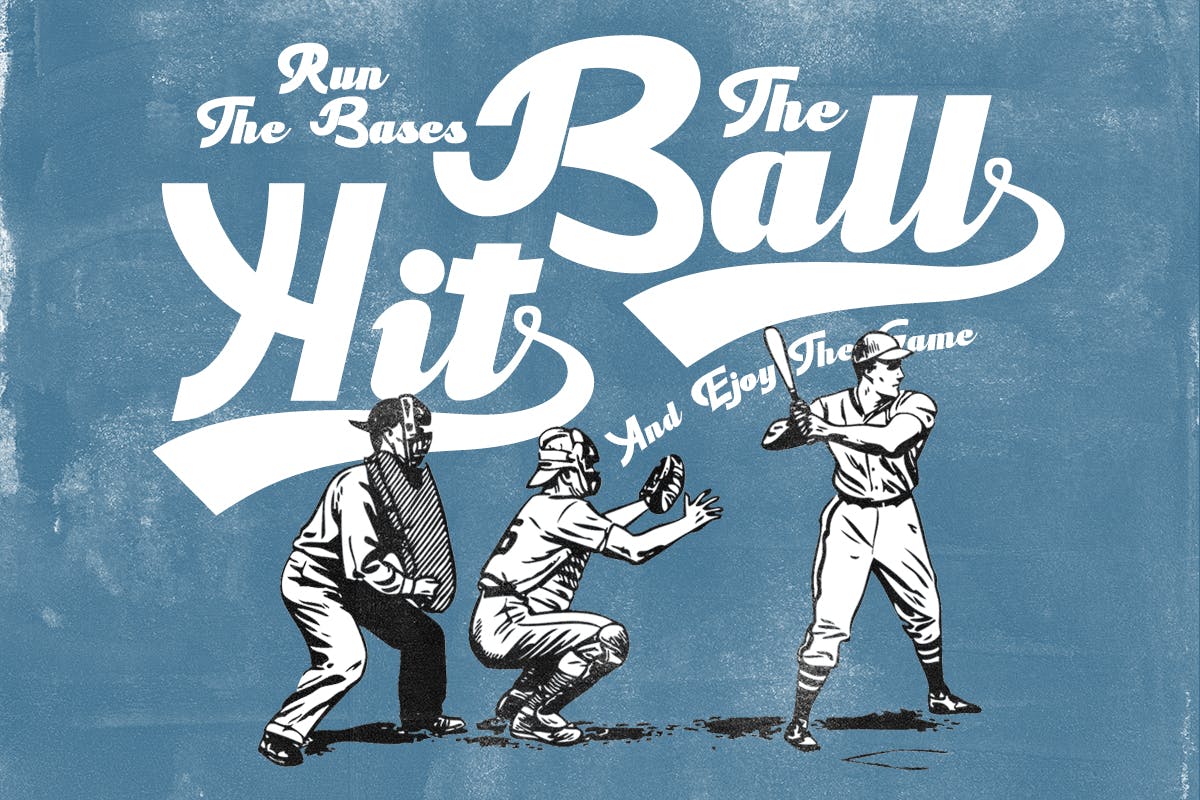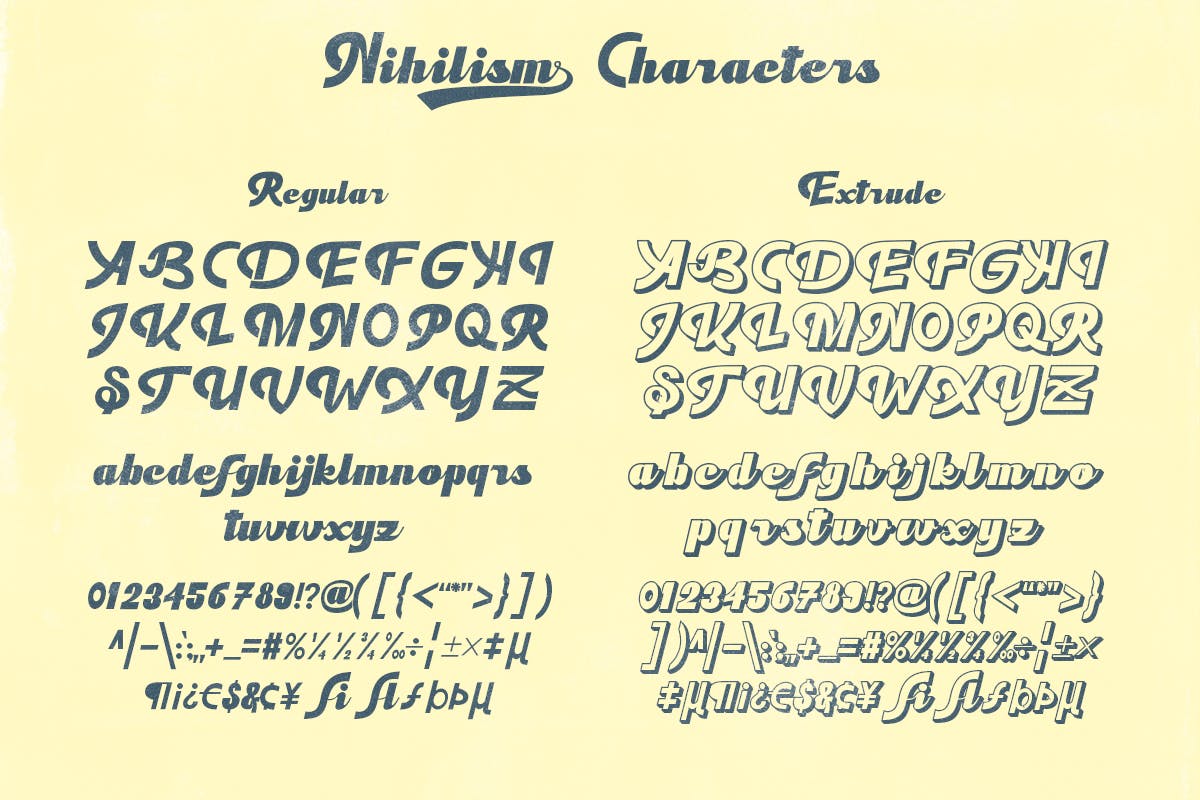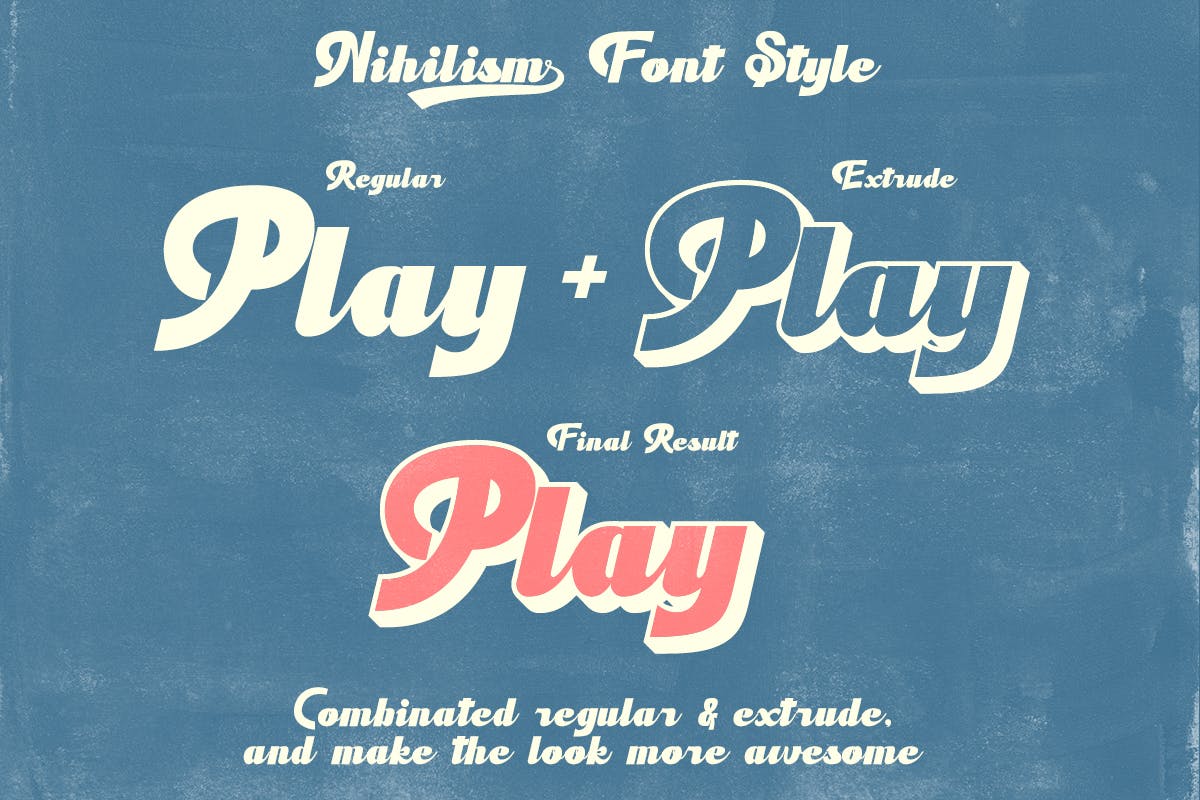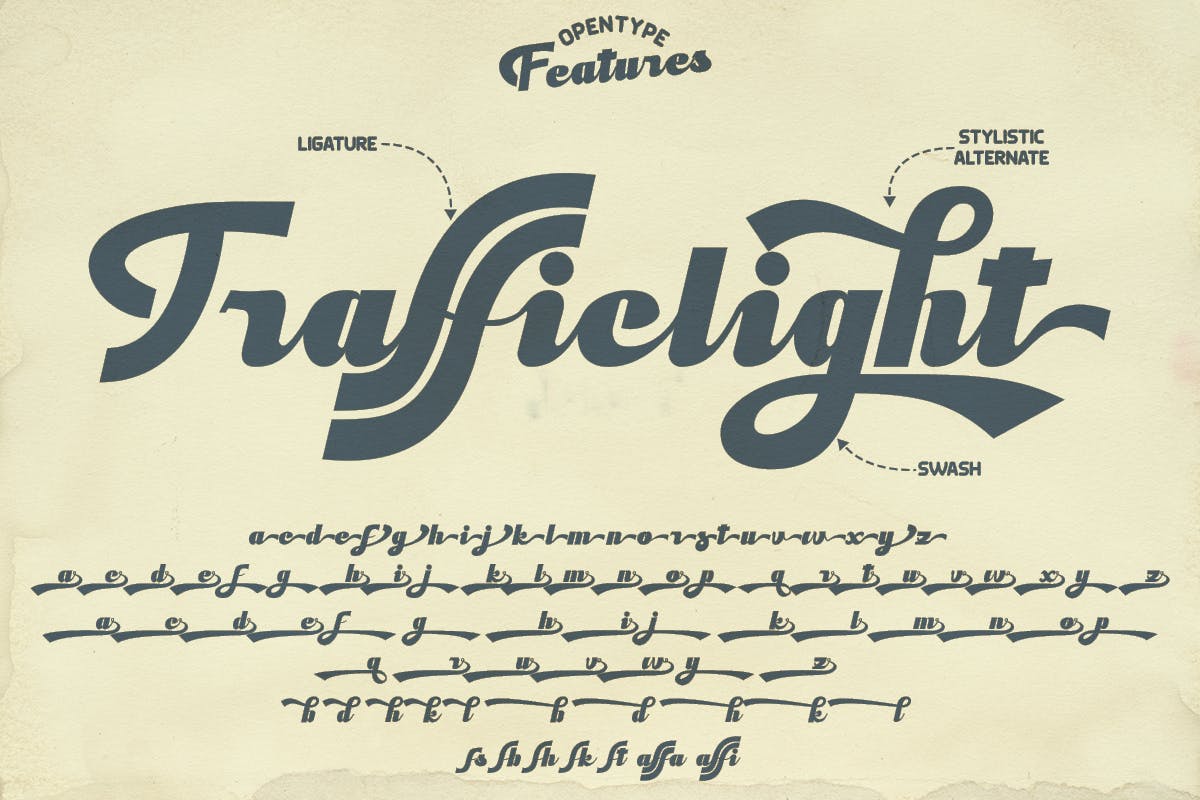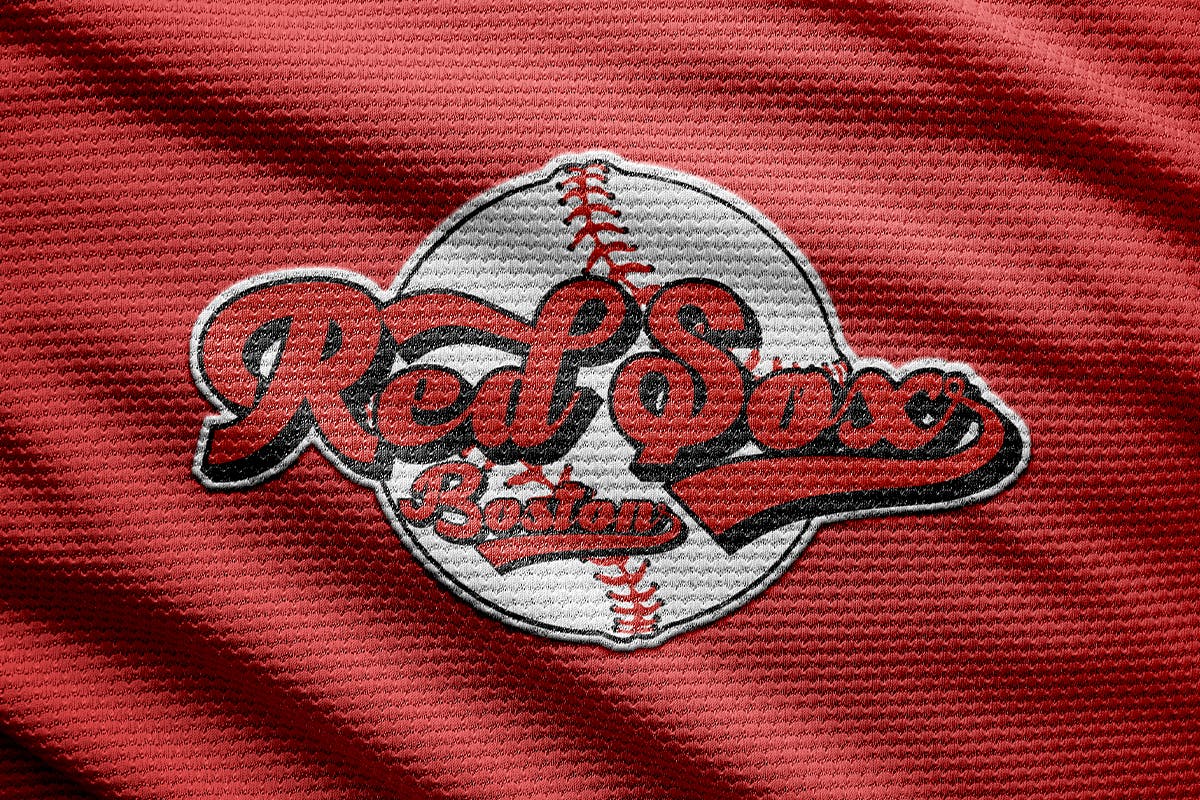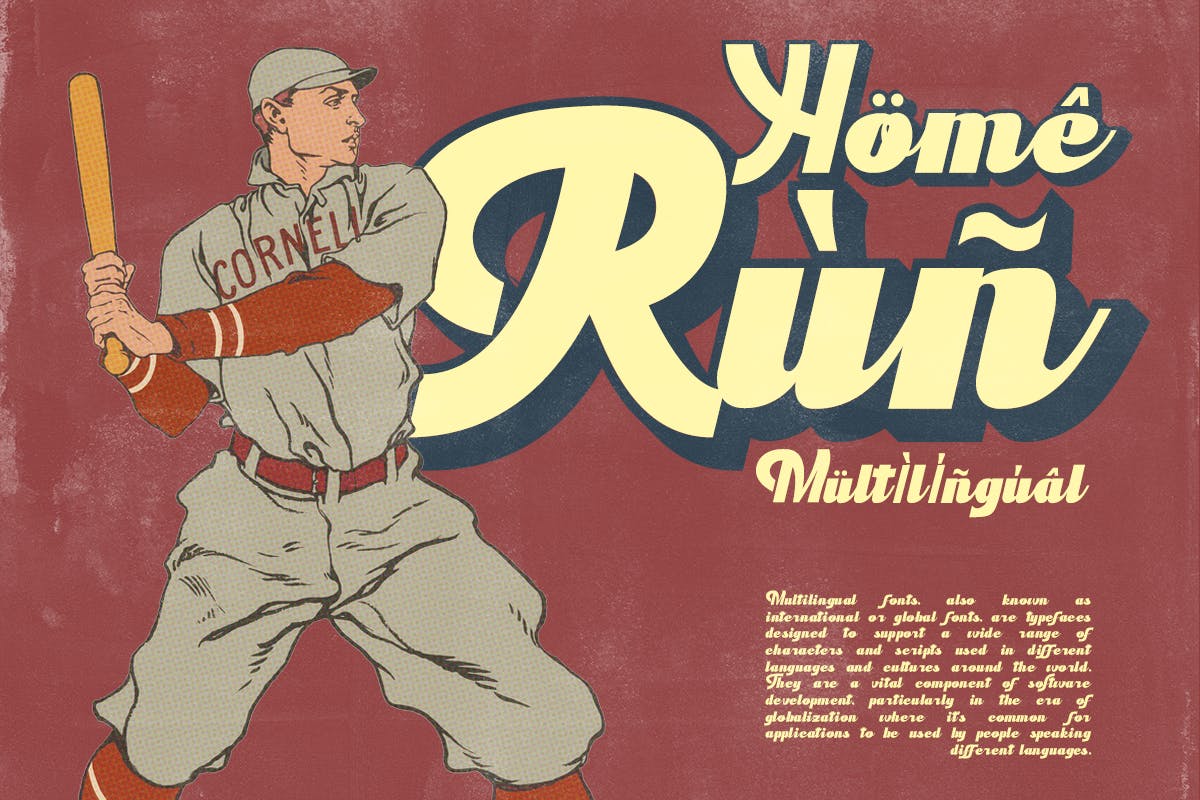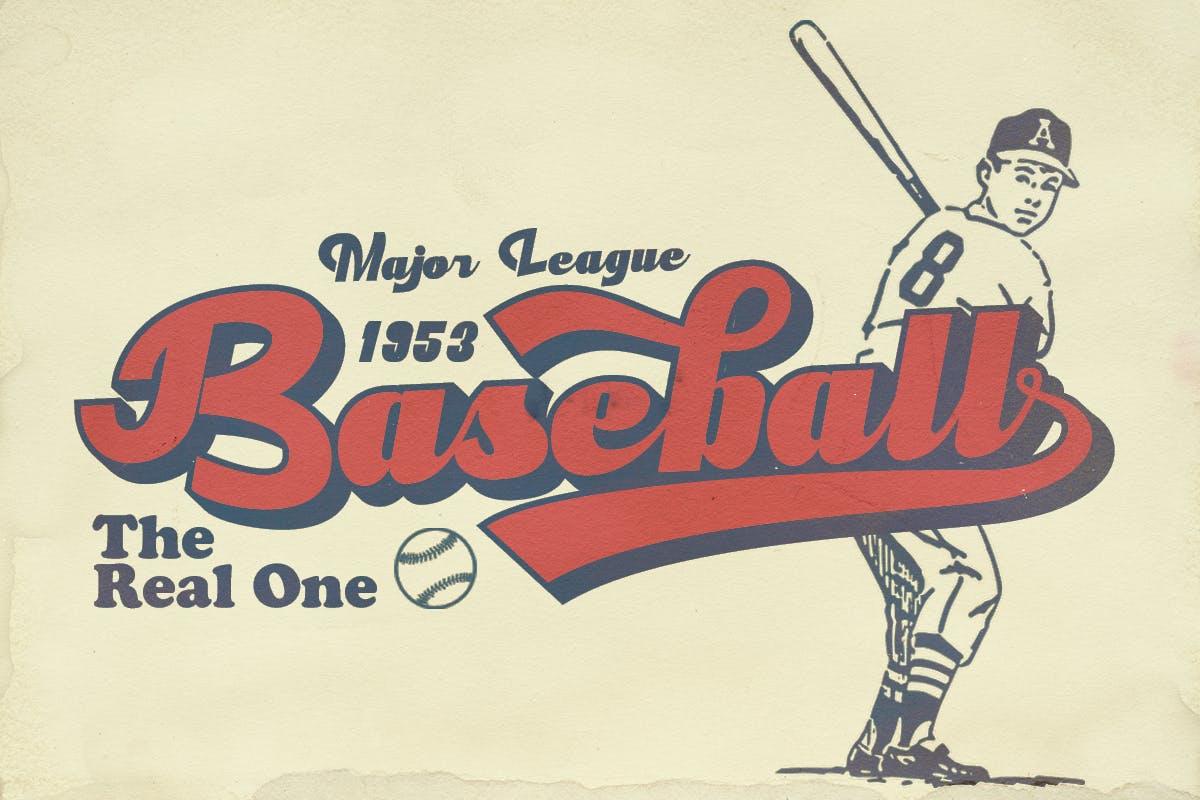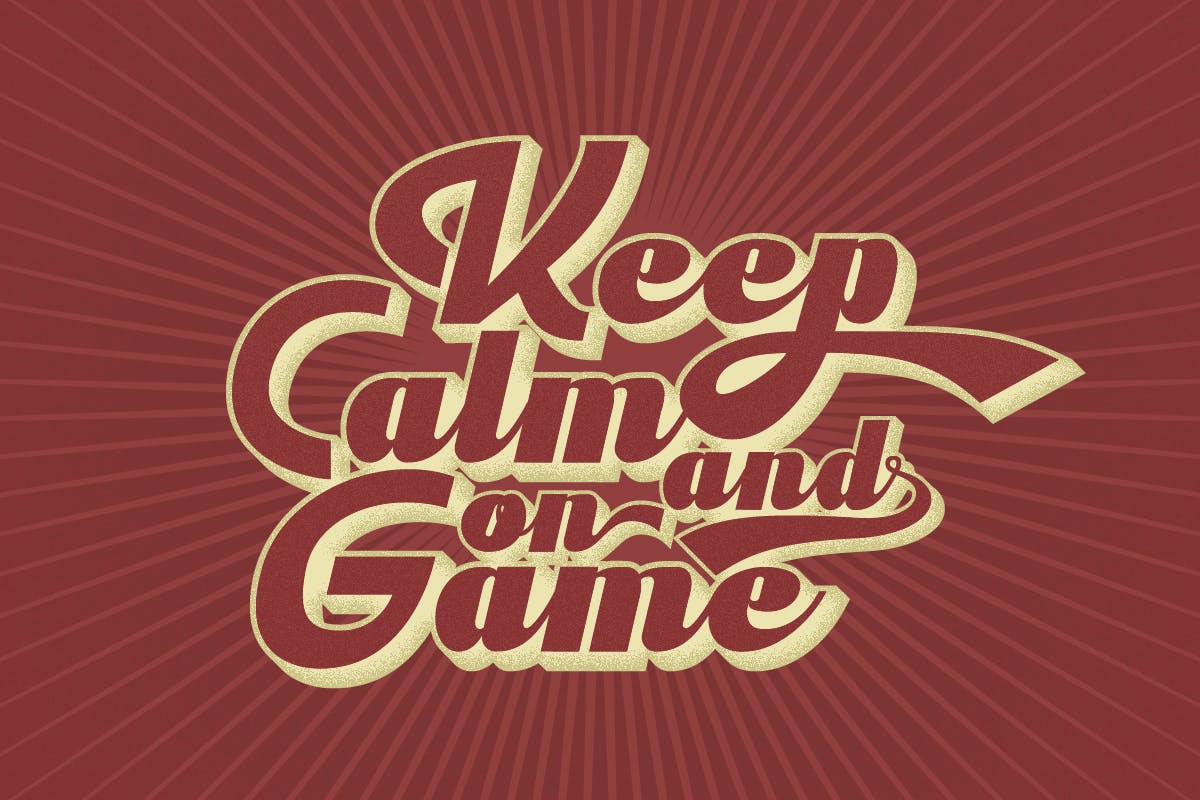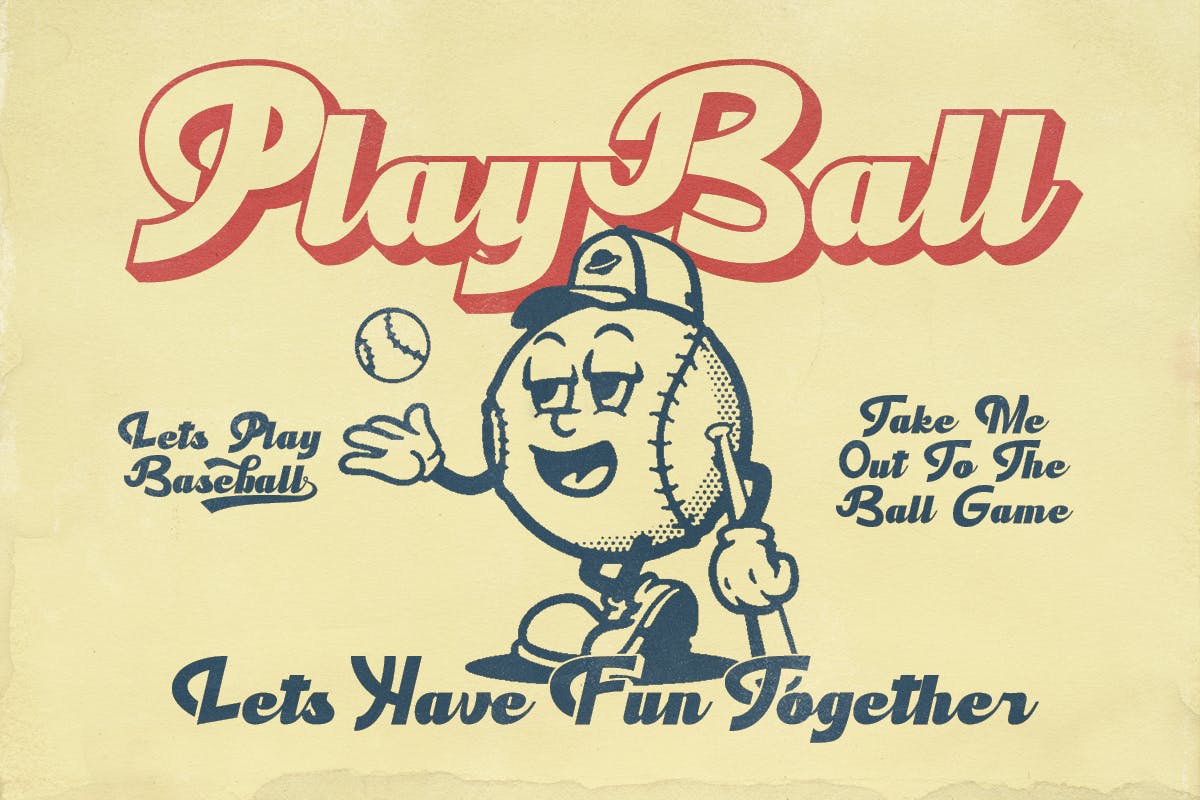
دانلود فونت اسکریپت نیهیلیسم با طراحی خاص
Nihilism Crafted Script Font
فونت نیهیلیسم، انتخابی عالی برای طراحی‌های خاص و جذاب.
معرفی فونت نیهیلیسم، یک فونت اسکریپت با طراحی دقیق که تعادل کاملی بین منحنی‌های ظریف و شخصیت متمایز برقرار می‌کند. این فونت برای طراحی لوگوهایی که تأثیر ماندگاری دارند، طراحی پوسترهای جذاب و بسیاری پروژه‌های دیگر ایده‌آل است. بگذارید نیهیلیسم به طراحی‌های شما جذابیت و سبک خاصی ببخشد.
• دارای 2 سبک: معمولی و برجسته